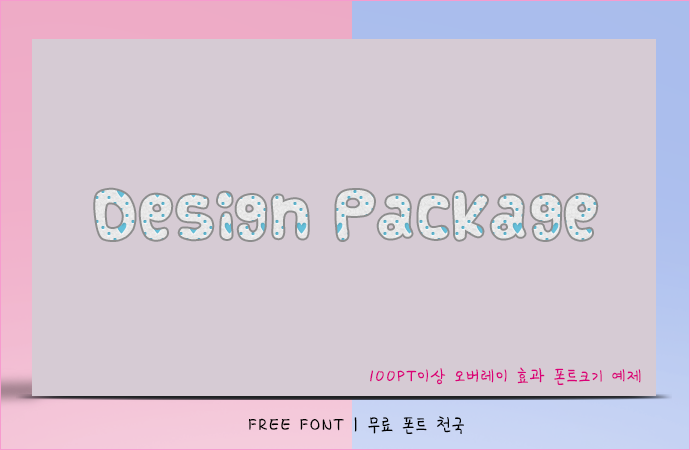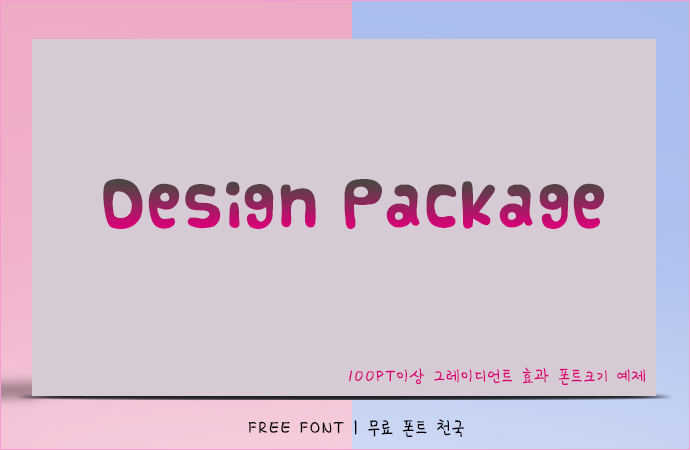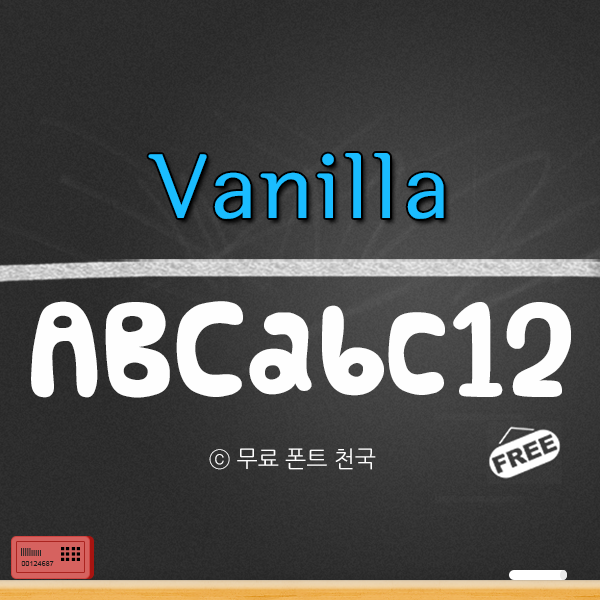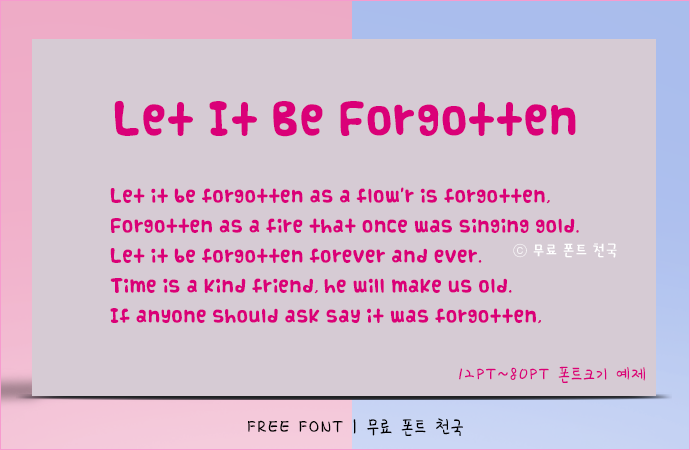
부풀어 오른 풍선 스타일의 Vanilla 영문 폰트
뚱뚱하고 부풀어 오른 풍선 느낌이 드는 Vanilla 영문 폰트입니다. 글자체 하나하나 굵기가 굵어 16pt 이하의 크기에서는 그렇게 추천드리지 않습니다. 큰 제목 혹은 머리말과 같은 크기에 좋은 가독성을 보이는 서체입니다. 귀여움이나 장난스러운 분위기의 폰트가 필요할 때에도 추천드리는 서체입니다. Vanilla 폰트는 누구나 자유롭게 사용 가능한 무료 폰트입니다.
Vanilla 폰트 # 미리보기
Vanilla 폰트, 12~80PT 크기로 적용한 효과
Vanilla 폰트, 100PT 크기 이상으로 작업한 오버레이 효과
Vanilla 폰트, 100PT 크기 이상으로 작업한 그레이언트 효과